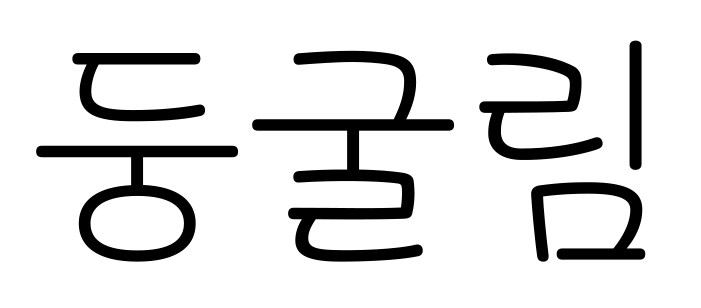
돼지꼬리 같은 모양의 ‘ㅂ’, 가로획과 빗침을 한 번에 쓴 듯한 모양의 ‘ㅈ’과 ‘ㅊ’, 과감하게 위에서 아래로 내리그으며 시작하는 ‘ㄹ’ 등 대체적으로 자음이 개성 있게 표현되었으며, 그에 비해 직선적으로 디자인 된 모음이 폰트의 단정한 인상을 잡아준다.
얇은 웨이트를 갖고 있기 때문에 너무 크게 쓰면 주목도가 떨어질 수 있으니 작게 사용하는 것이 좋다. 동화책, 펜으로 그린 듯한 웹툰과도 잘 어울린다.
Adobe-KR-9 규격이 적용되어 기존에 표현이 어려웠던 뷁, 똠얌꿍 같은 표현들이 가능해졌다.